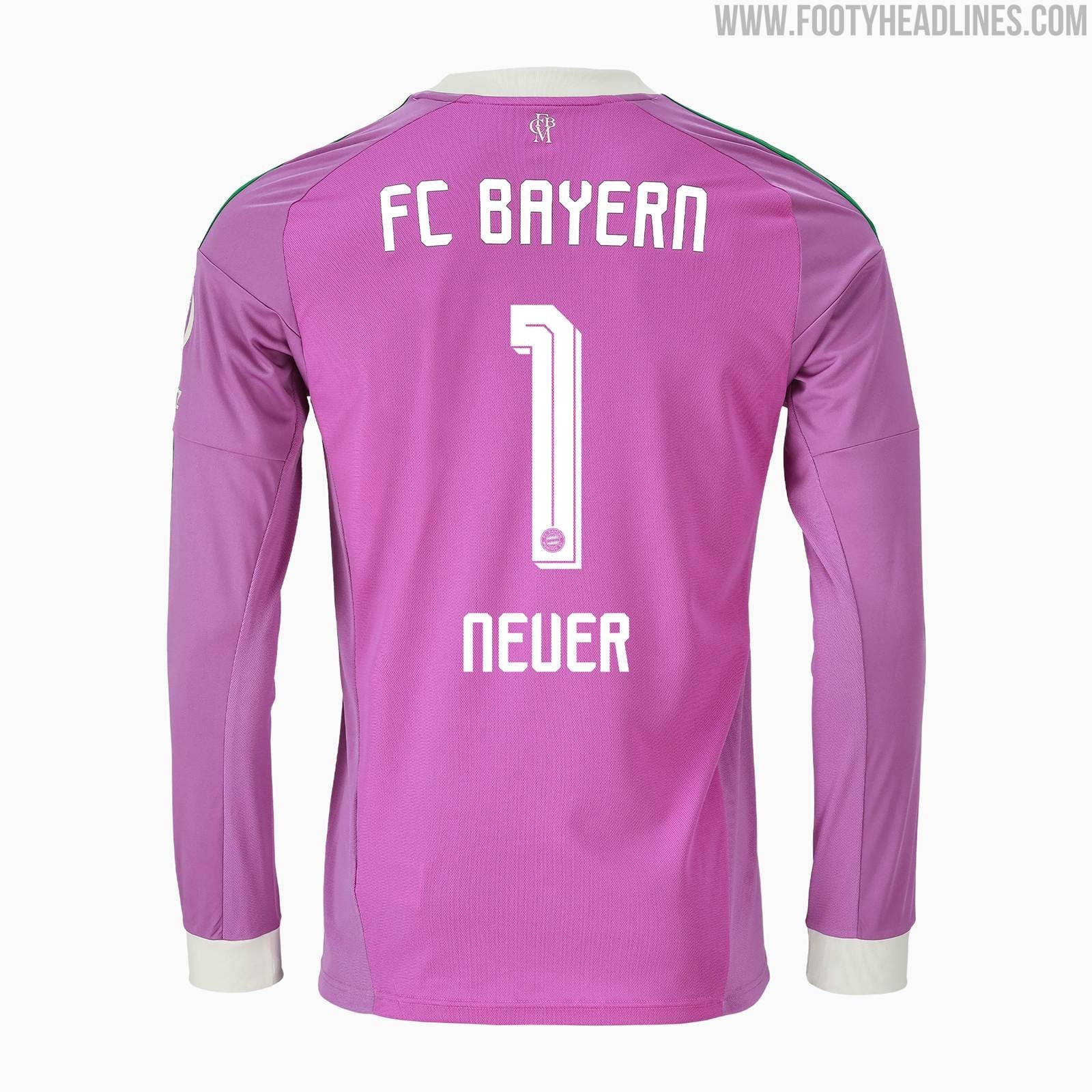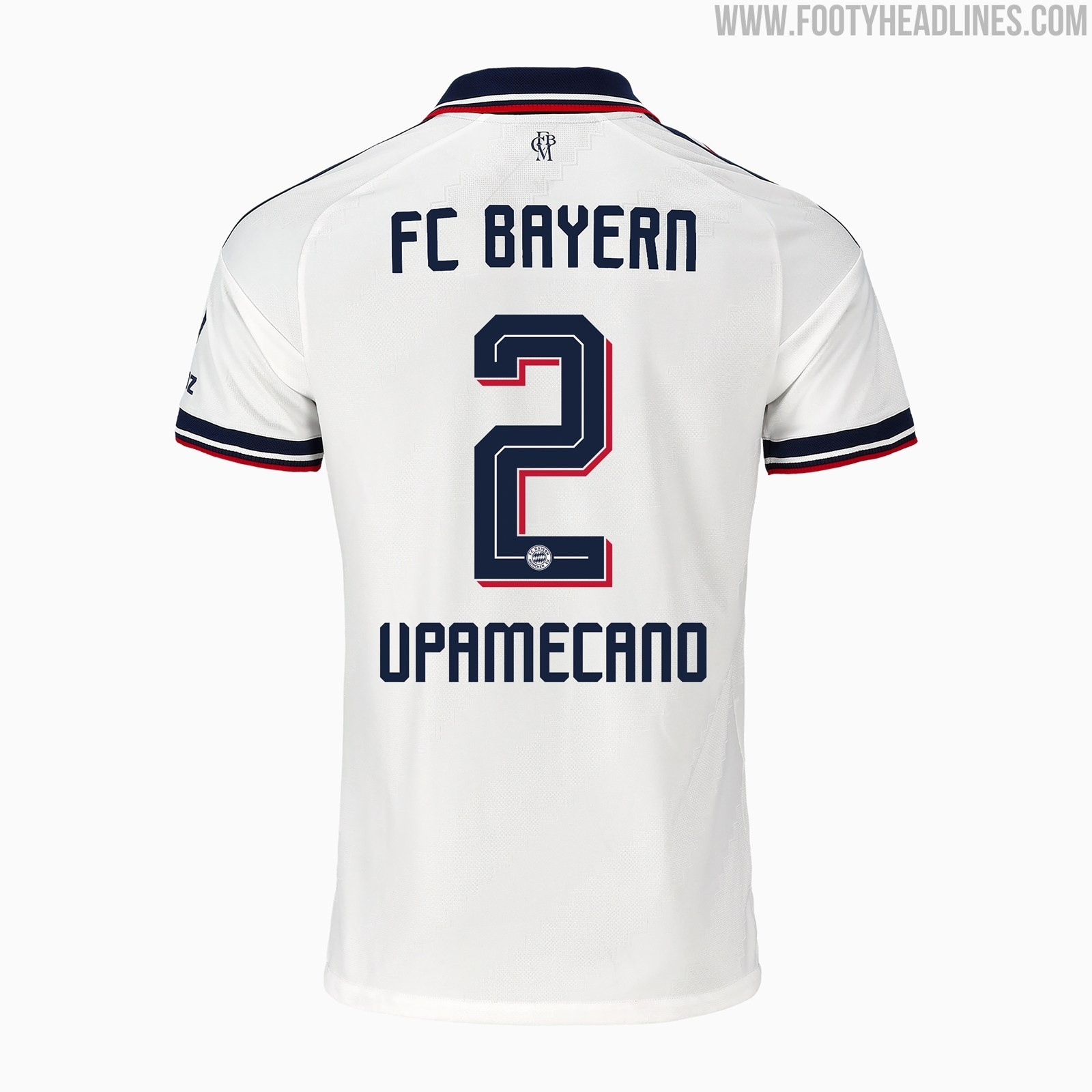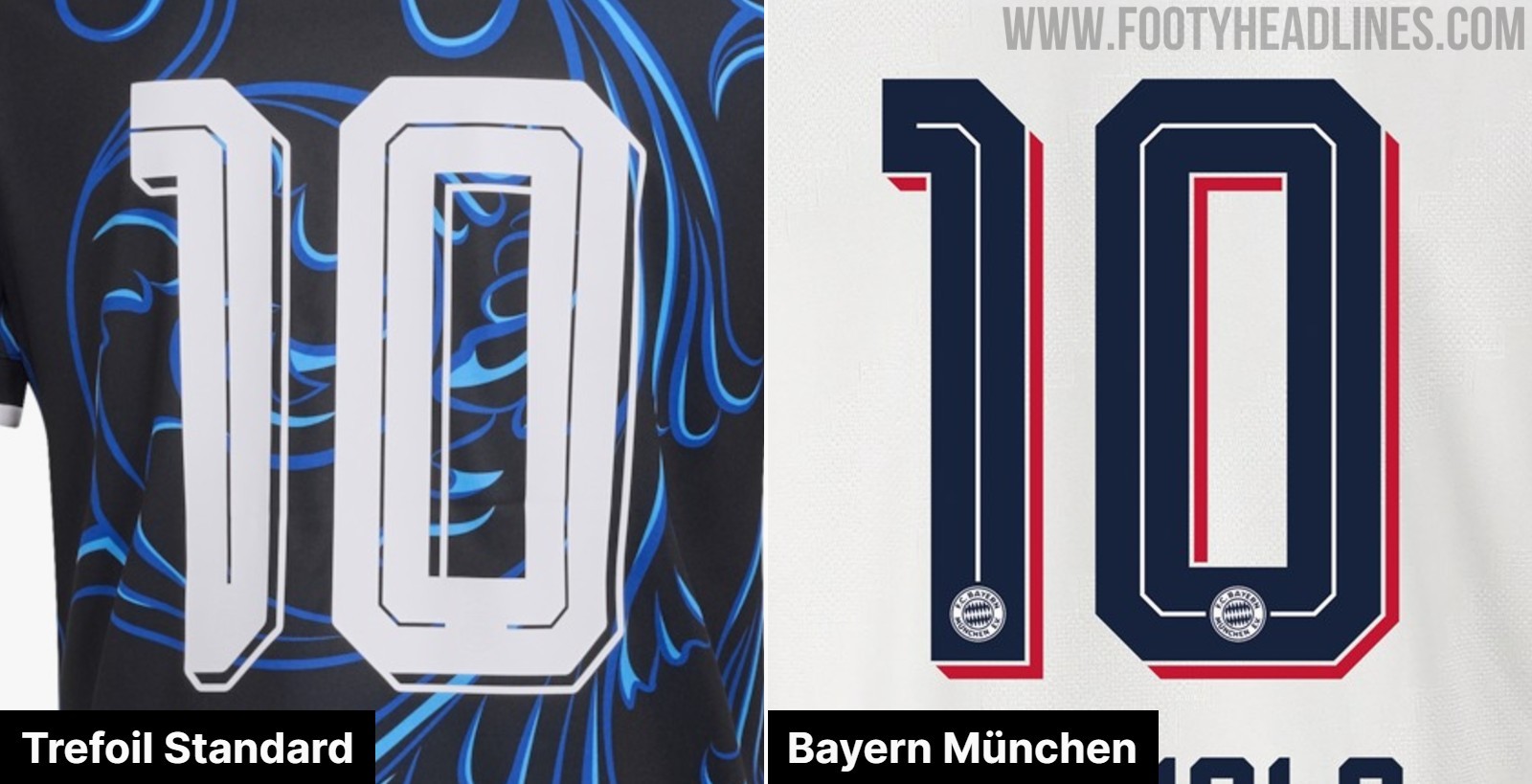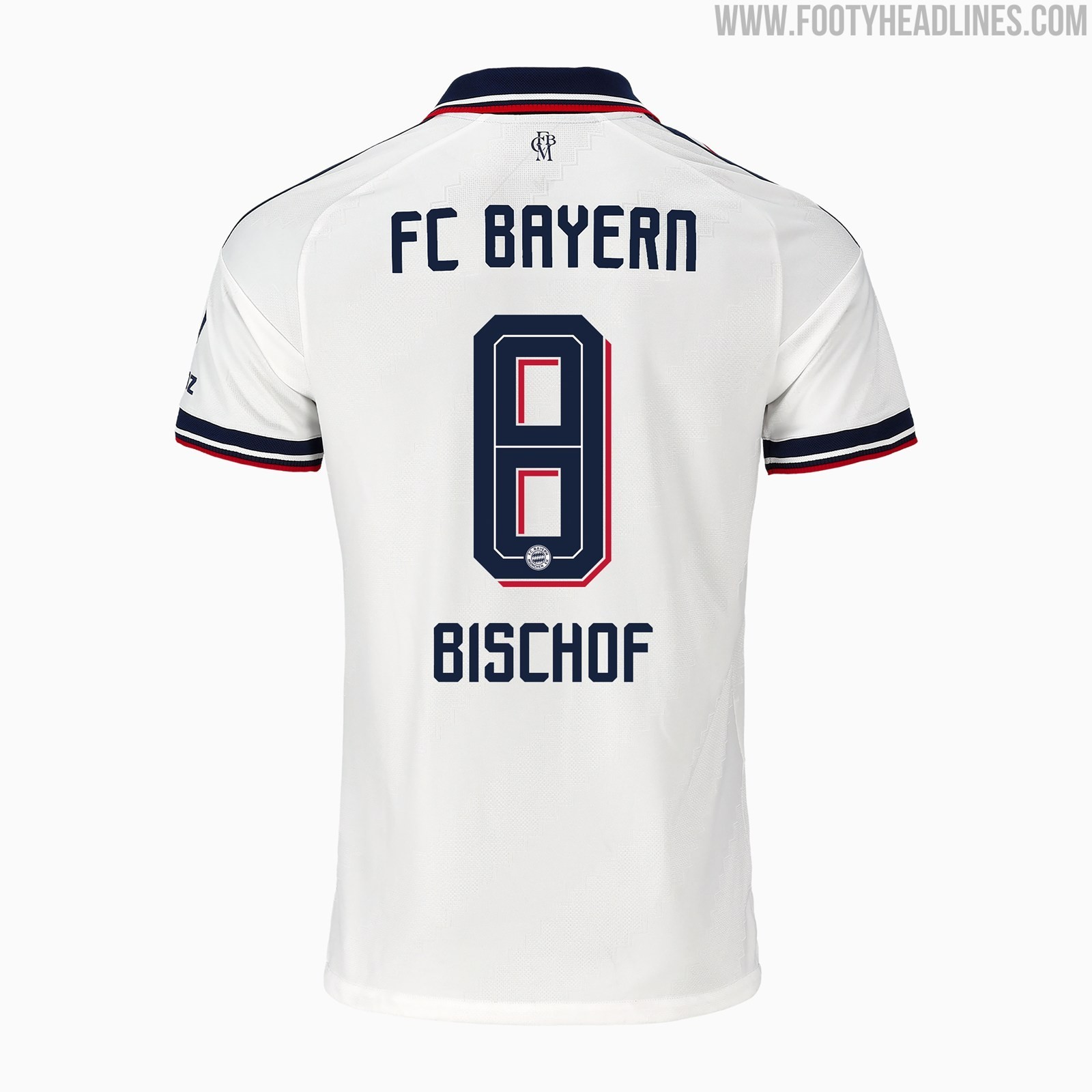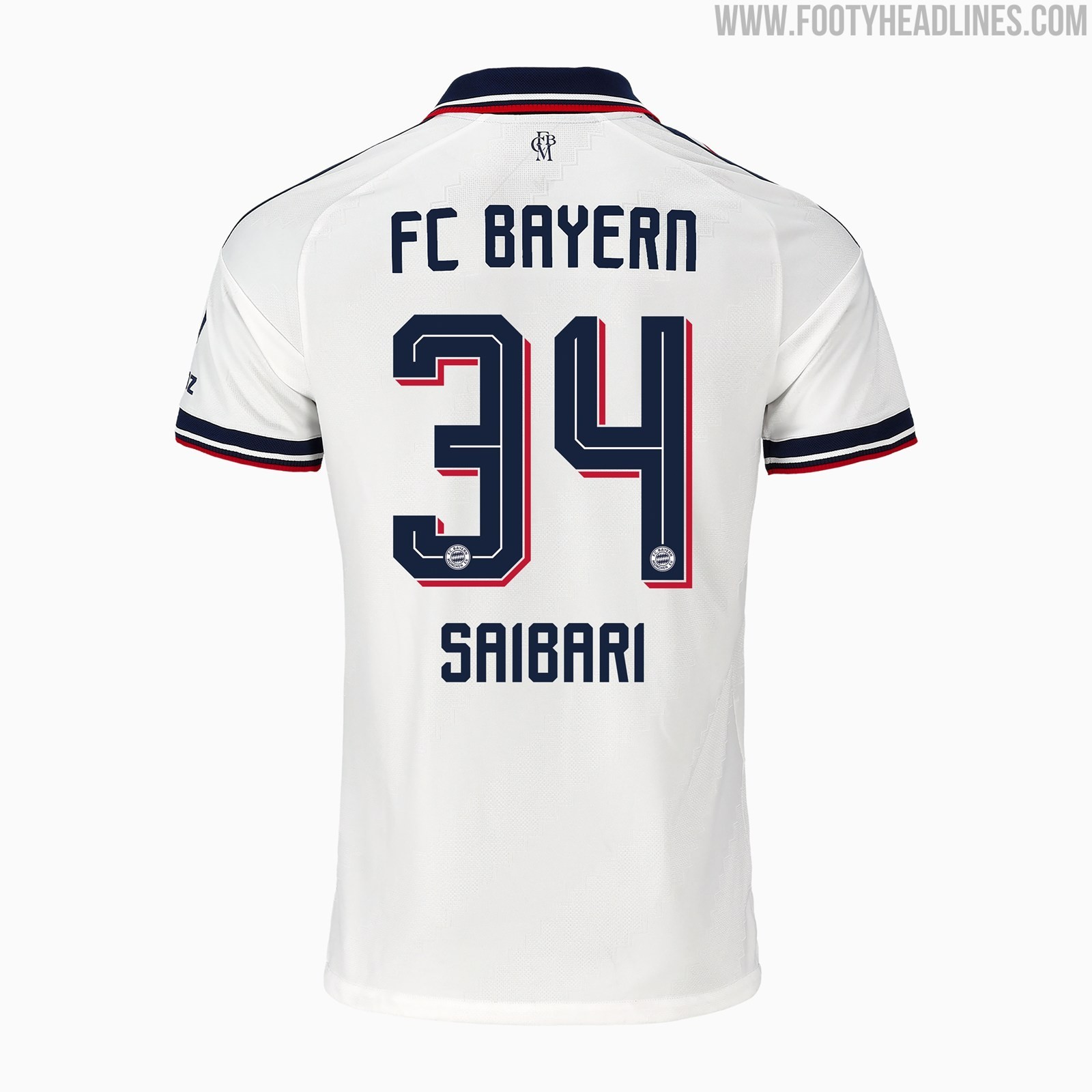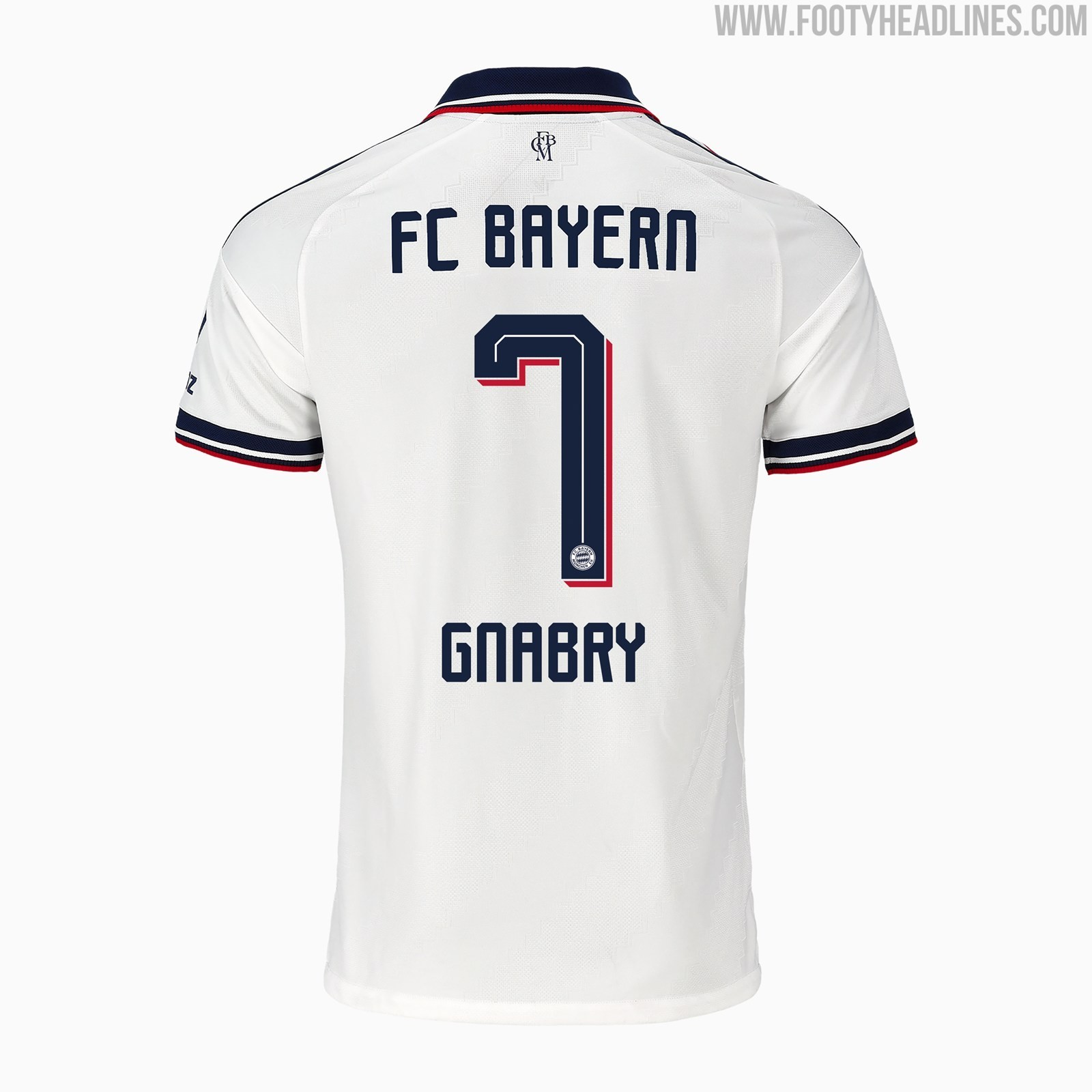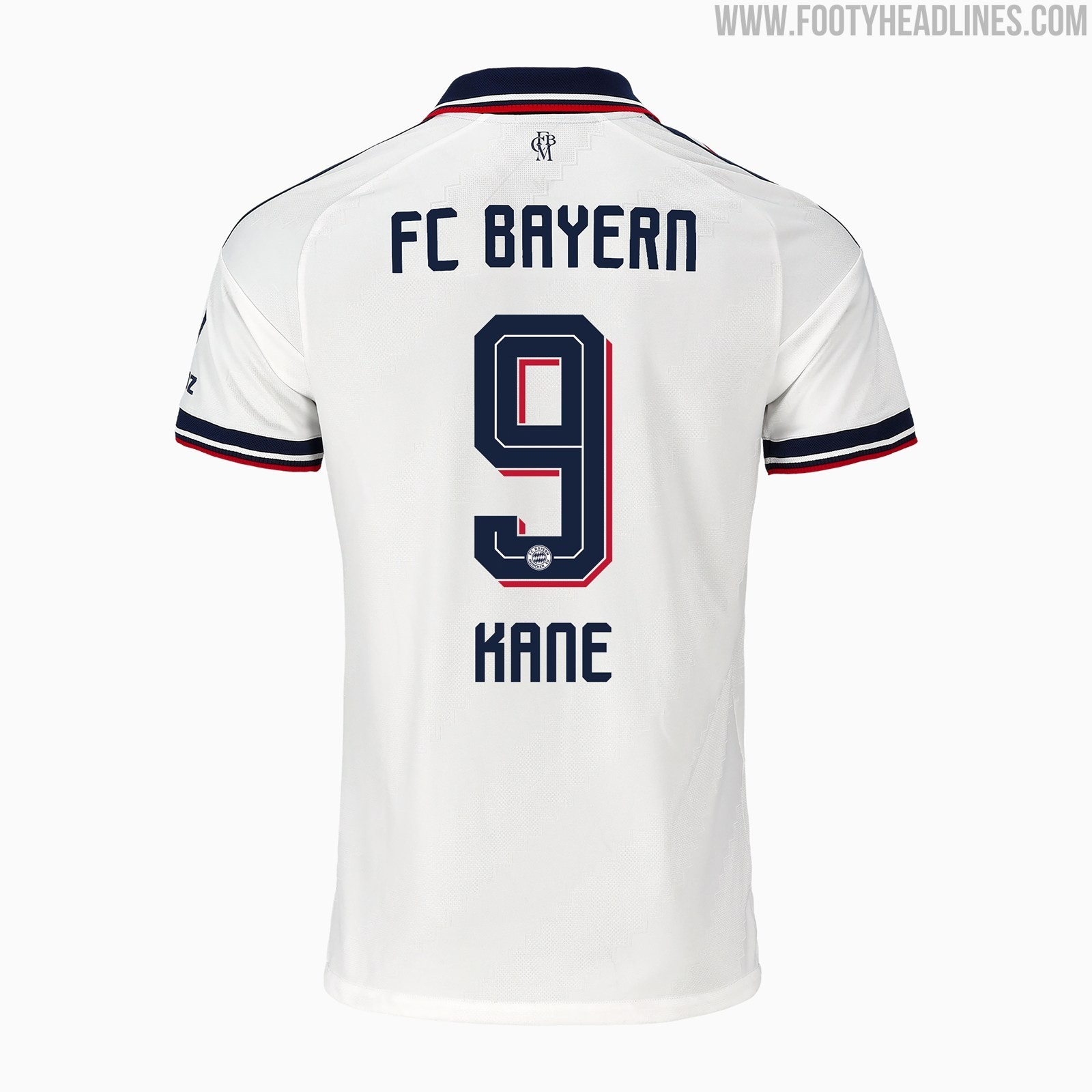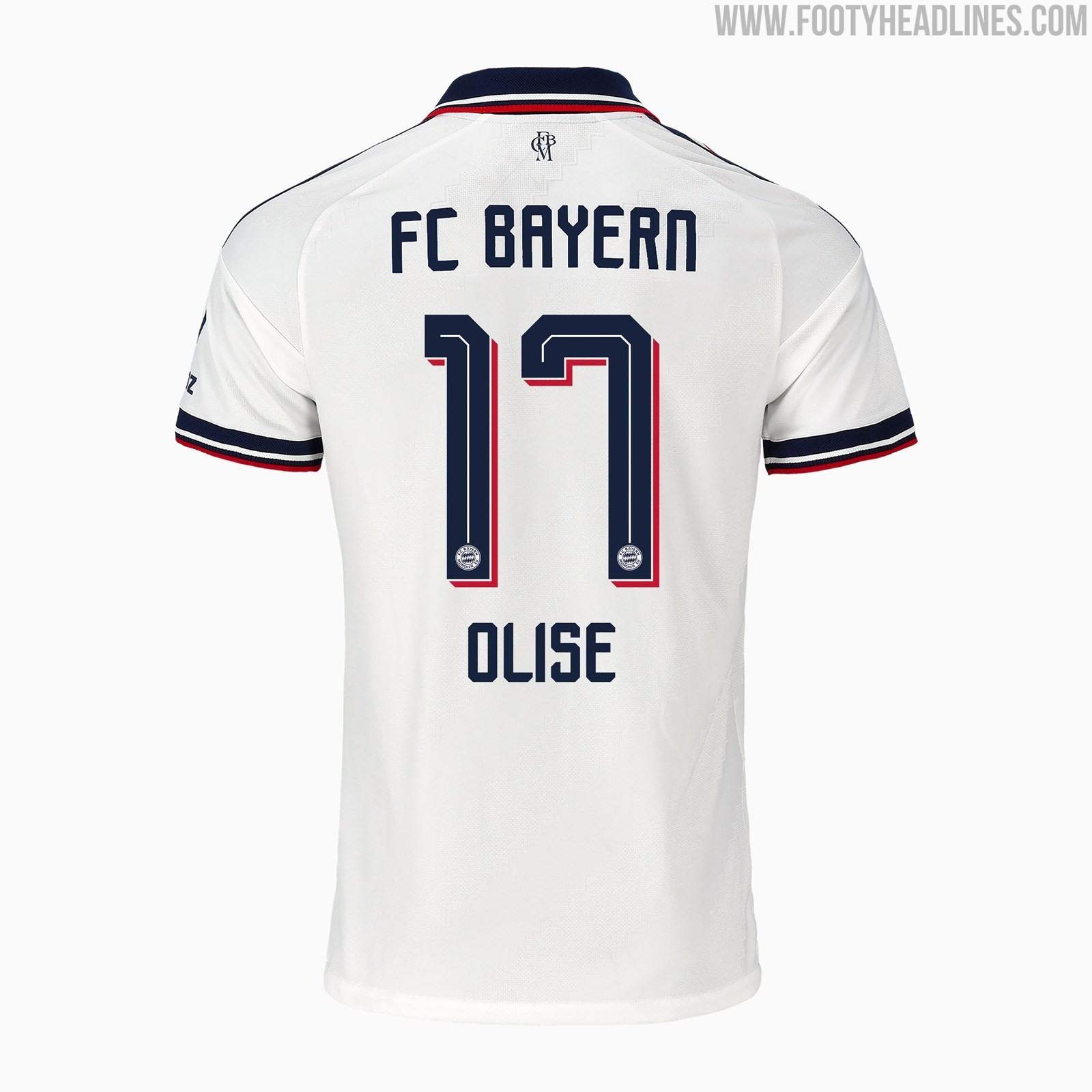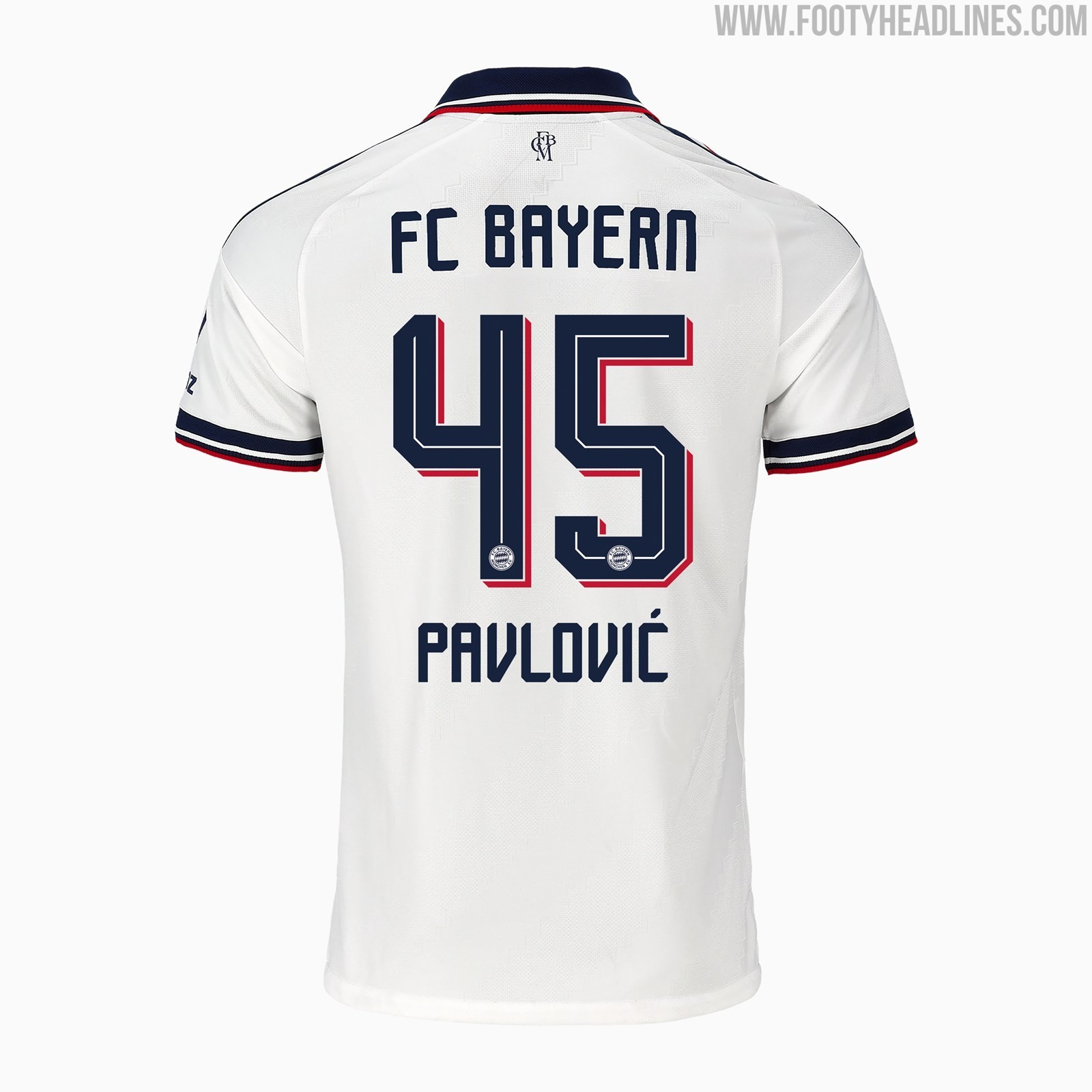
Rivelato il font della seconda maglia del Bayern Monaco 26-27
• Rivelato il Font: Il font personalizzato per la seconda maglia del Bayern Monaco 26-27 è stato svelato dopo il lancio ufficiale della maglia stessa.
• Design della Maglia: La maglia presenta una base bianca con dettagli rossi e blu navy, incorporando lo stemma classico “e.V.” del club e il logo Adidas a trifoglio, con nomi e numeri che riflettono un'estetica retrò.
• Somiglianza del Carattere: Il carattere utilizzato è quasi identico al font semplificato Adidas “Trefoil Standard” dei Mondiali 2026, con minime differenze, come nella parte inferiore del numero 1, e adattato nei colori per abbinarsi al design della maglia.
Dopo il lancio ufficiale della seconda maglia del Bayern Monaco 26-27, ti mostriamo in dettaglio il font personalizzato usato per la nuova maglia. La maglia ha una base bianca con dettagli in rosso e blu navy, e riporta in primo piano il classico stemma del club “e.V.” insieme al logo a trifoglio di Adidas. I nomi e i numeri dei giocatori sul retro si abbinano perfettamente a questa estetica di ispirazione retrò.
Rivelato il font della seconda maglia del Bayern Monaco 26-27
Il carattere utilizzato per la seconda maglia del Bayern Monaco 26-27 è quasi identico a quello semplificato di Adidas per i Mondiali del 2026, spesso chiamato “Trefoil Standard”.
Un confronto diretto tra una maglia standard Adidas Trefoil di Messi e la nuova maglia di Musiala mette in evidenza la tipografia molto simile. Utilizza esattamente la stessa struttura classica a caratteri squadrati e gli stessi dettagli in linea, adattando la combinazione di colori per abbinarsi al design blu navy e rosso del Bayern. Il numero 1, ad esempio, presenta una piccola differenza nella parte inferiore.